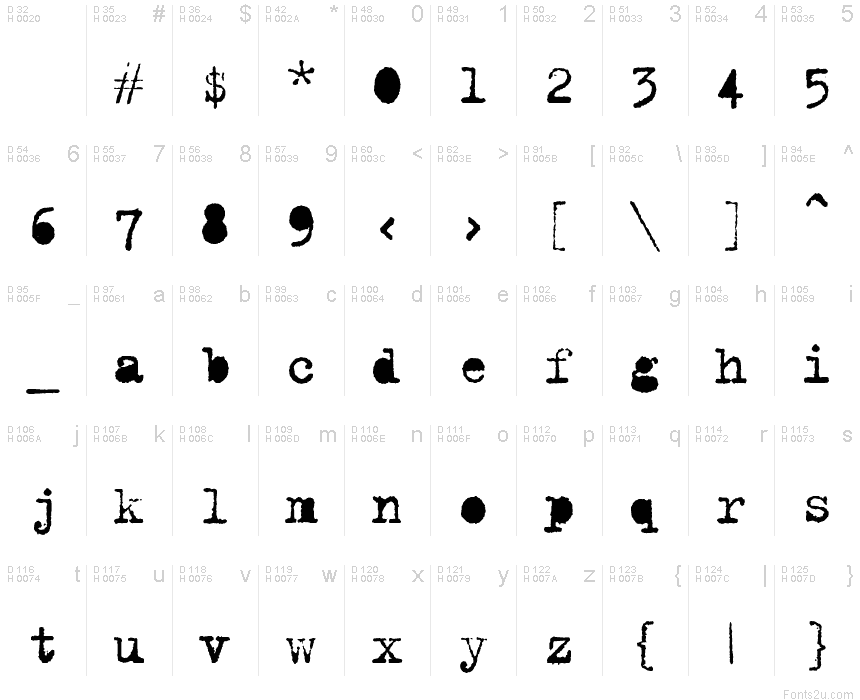
Trixie Extra autorstwa Erika van Bloklanda z LettEror to darmowy, mocno wyeksploatowany krój typu display w starym stylu. Oddaje surowość, "przegryziony" tuszem charakter liter ze starych maszyn do pisania. Litery są krępe i solidne, ale ich krawędzie drżą, odpryskują i rozmazują się dokładnie na tyle, by nadać całemu krojowi zadziorny, "żywy" wyraz, zamiast sterylnego, odtwórczego wykończenia.
Idealnie sprawdzi się na plakatach, w zinach, na okładkach płyt, opakowaniach w stylu pulp czy w redakcyjnych nagłówkach, gdzie darmowy font ma mieć w sobie nieco buntu i ludzkiego pierwiastka. Dzięki temu, że litery wyglądają jak odbite pieczątką, zużyte i nieco nieposłuszne, świetnie wypadają w krótkich nagłówkach, otwarciach rozdziałów czy logotypach, które potrzebują surowego, vintage’owego pazura.